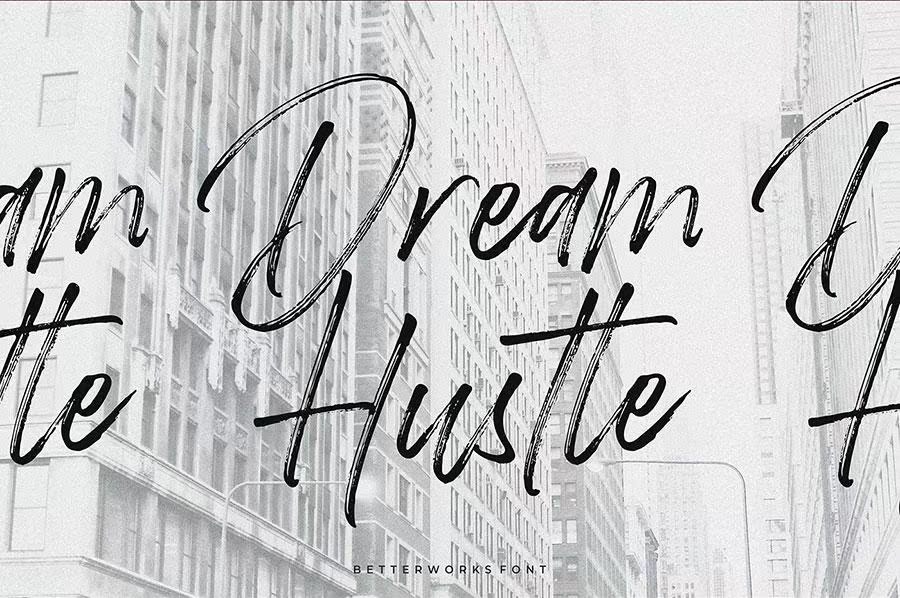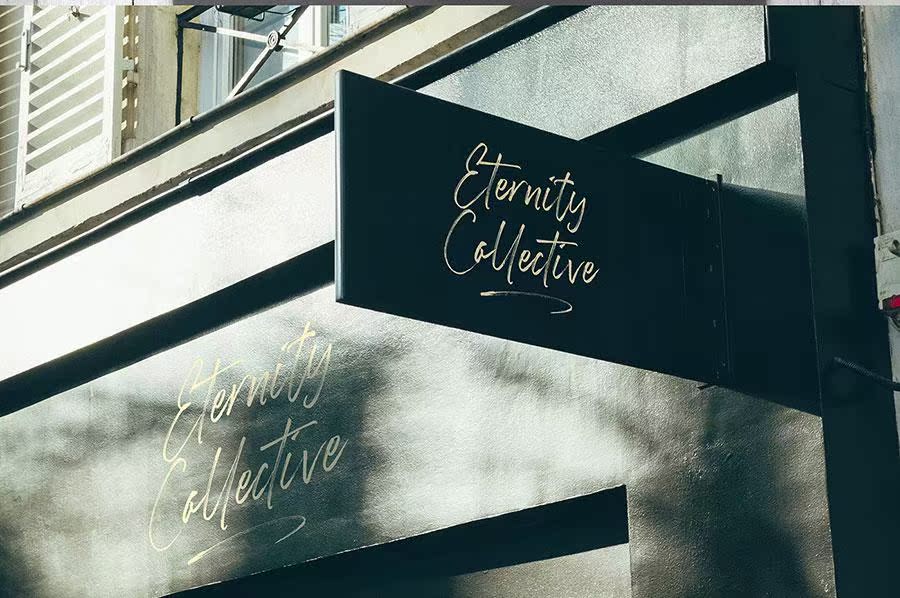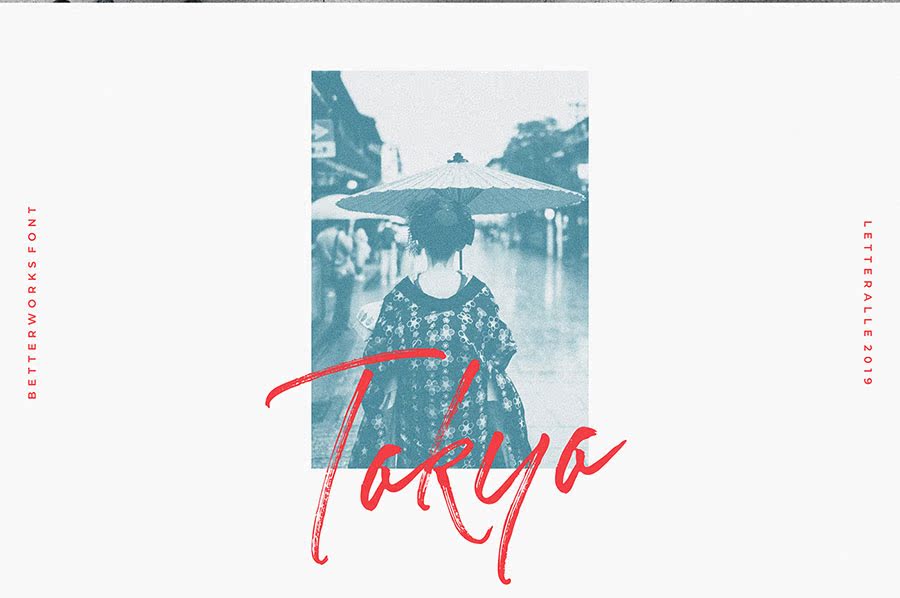
Better WorkScript Free Demois Modern and Charming and Brushed Font.Better Works必须使用可进行自然打印的详细图形。Better Works使用交替字体(大写和小写),您可以通过PentypeFeature或通过安装可通过A-I单独访问的交替字体文件和OSWash来访问。这是品牌、广告设计的完美之选,T恤衫、网站、杂志、包装、merch和许多其他产品。